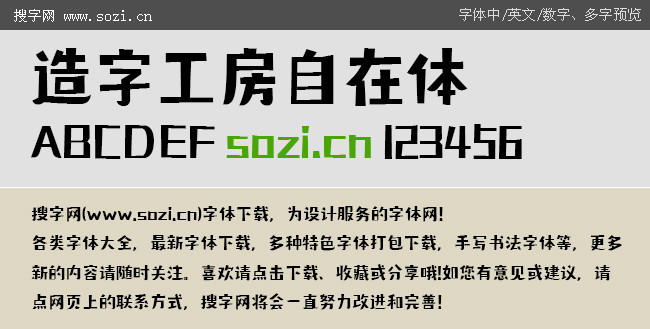
造字工房自在體
搜字網(wǎng)給大家提供一款造字工房自在體中文字體下載,造字工房自在體是一款適用性非常廣泛的中文字體,其筆畫特點(diǎn)生動(dòng),活潑俏皮,體勢(shì)靈動(dòng)自由,疏密有致,別具豐潤(rùn),兼具文藝雅致與質(zhì)樸幼拙,天真爛漫卡通可愛(ài),適合應(yīng)用于藝術(shù)設(shè)計(jì)、平面宣傳設(shè)計(jì)、網(wǎng)頁(yè)設(shè)計(jì)等應(yīng)用。(本字體為個(gè)人非商用版,如需要商用請(qǐng)聯(lián)系官方購(gòu)買版權(quán))